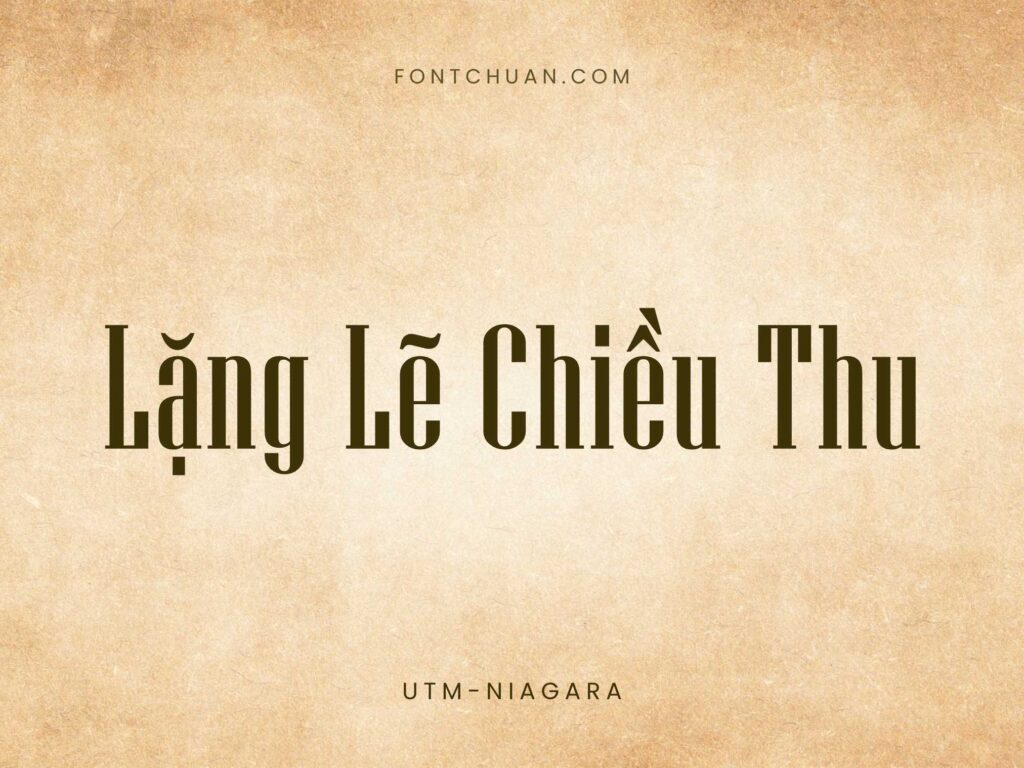
Font UTM Niagara Việt Hóa
UTM Niagara là một font chữ mang phong cách thanh mảnh và cao, tạo cảm giác sang trọng và hiện đại trong thiết kế. Font này nổi bật với các đường nét tinh tế, phù hợp với nhiều ứng dụng từ thiết kế tiêu đề đến in ấn chuyên nghiệp. Font đã được Việt hóa để hỗ trợ tiếng Việt, giúp mở rộng khả năng ứng dụng. Thành viên của Font Chuẩn đã sưu tầm và giới thiệu font này nhằm đáp ứng nhu cầu bạn đọc, cung cấp nguồn tham khảo chất lượng và ứng dụng thực tế vào các dự án thiết kế
Về đặc điểm thiết kế, UTM Niagara có kiểu dáng chữ hẹp, độ cao lớn và đường nét thanh thoát, giúp tạo sự khác biệt trong các thiết kế đồ họa. Font này phù hợp với nhiều ứng dụng như thiết kế poster, banner, tiêu đề, bao bì sản phẩm và nội dung quảng cáo. Các ngành nghề như quảng cáo, ẩm thực, thiệp cưới và công nghệ có thể tận dụng font này để tạo điểm nhấn trong các ấn phẩm thiết kế